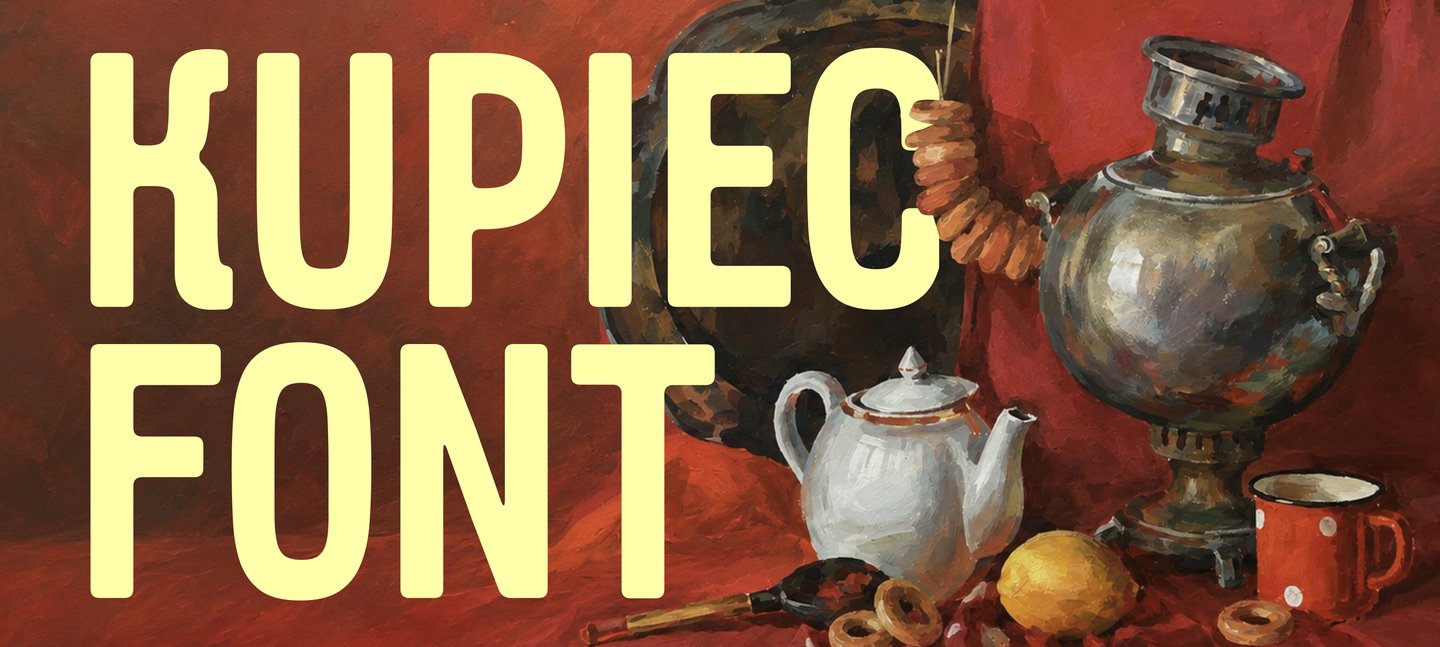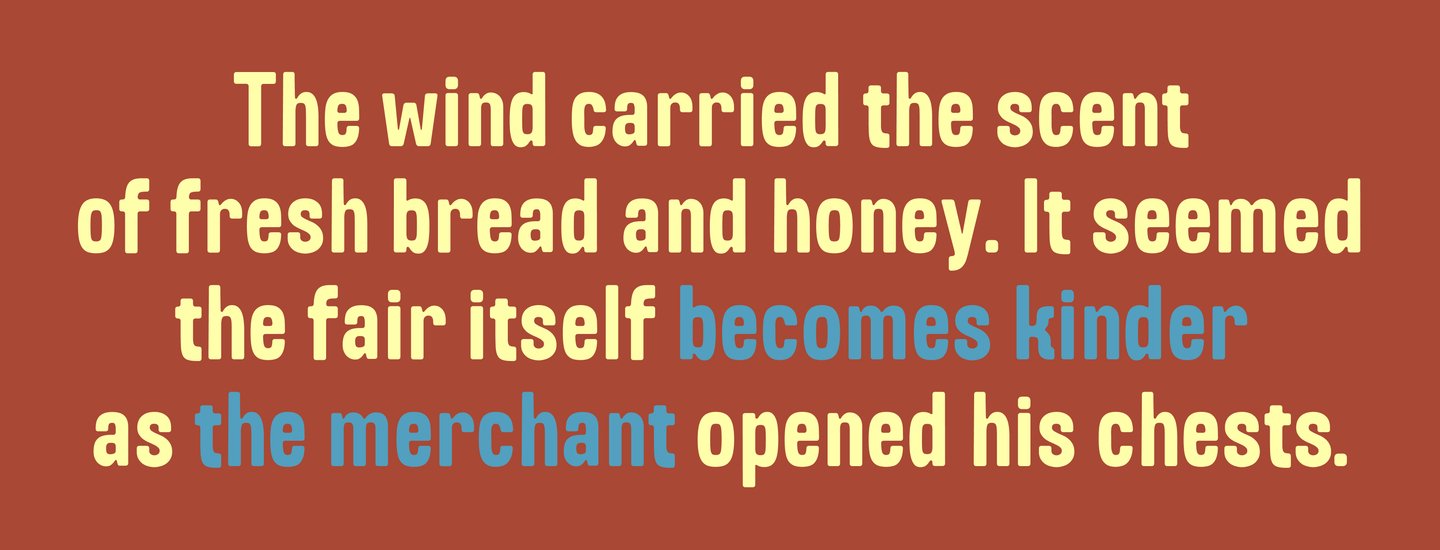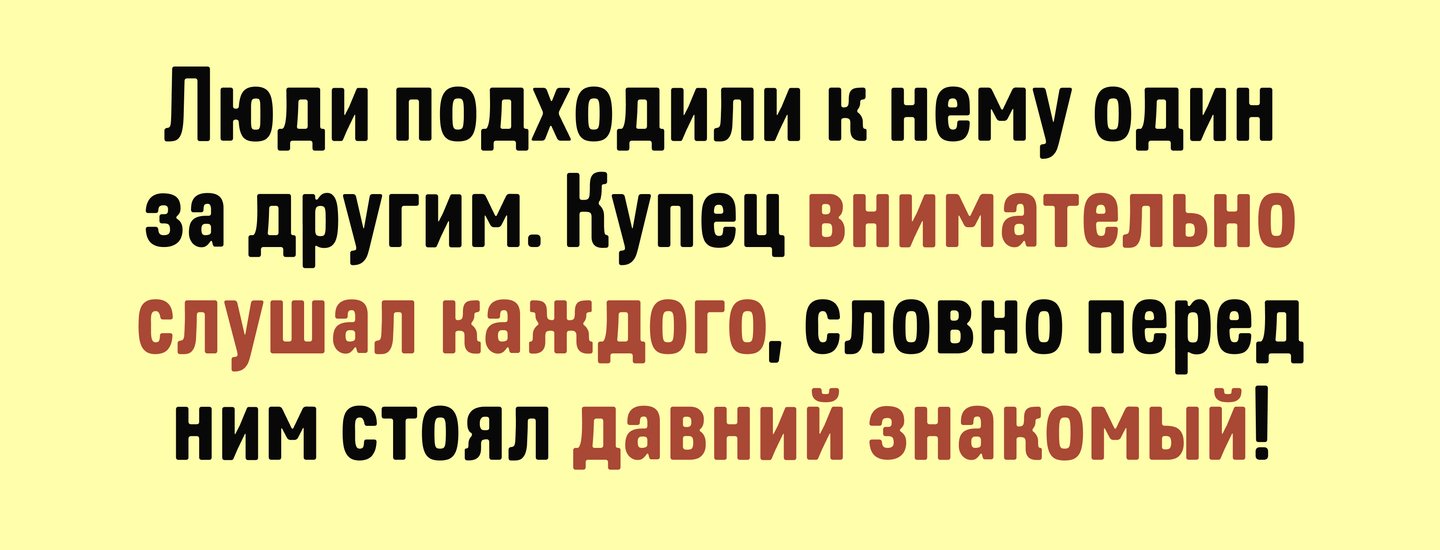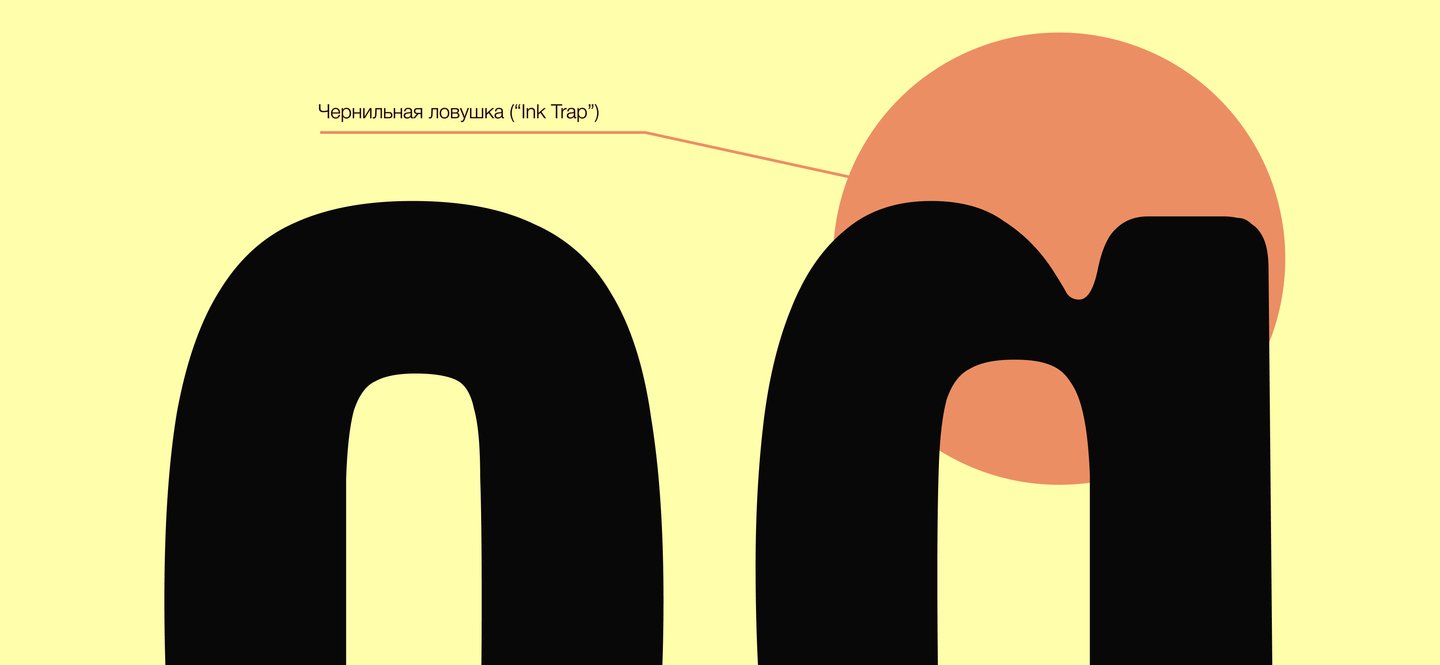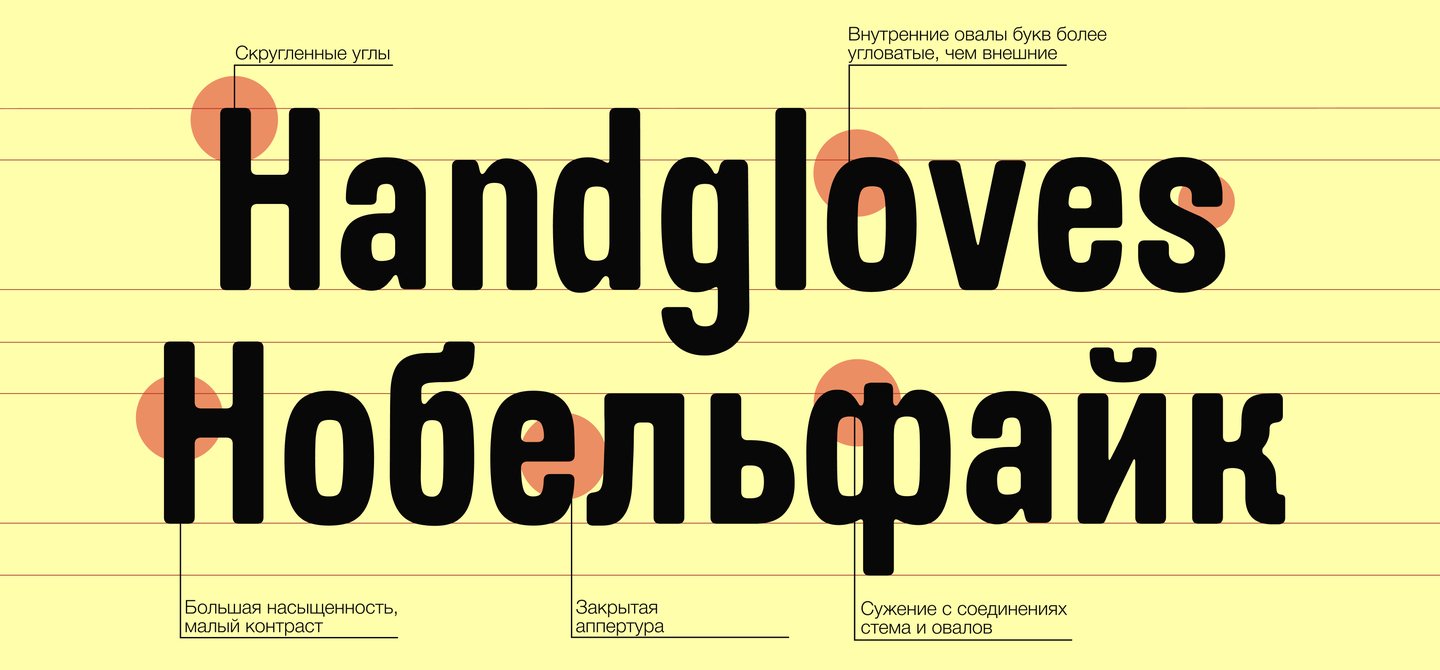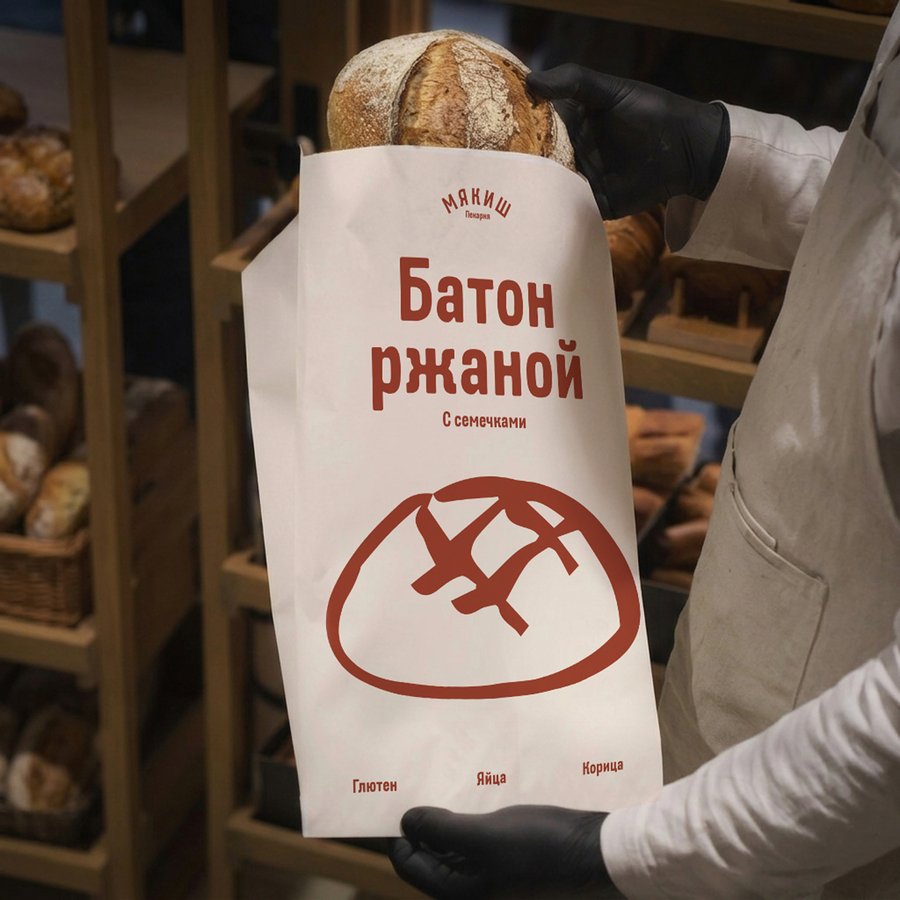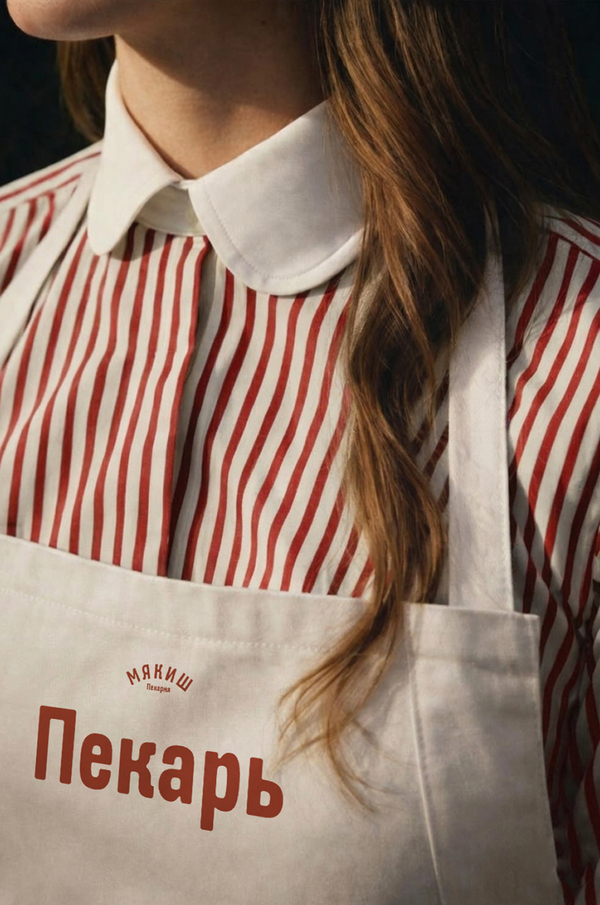
KUPIEC FONT
Kupiec — это насыщенный гротеск с мягким и дружелюбным характером, который как настоящий купец, знает как найти подход к любому, несмотря на языковые барьеры. Шрифт отлично подходит для наборного текста и заголовков.
Созданный в качестве дополнения к яркому акцидентному гротеску Jarmarek, шрифт Kupiec перенял некоторые его характерные черты, потому они идеально выглядят в паре с друг другом!
Касса знаков из расширенной кириллицы и латиницы.
Касса знаков из современного греческого.
При создании шрифта, чтобы все расширенные кассы получились достоверными и правильными, я частично опиралась на шрифт от компании Paratype, Pragmatica.